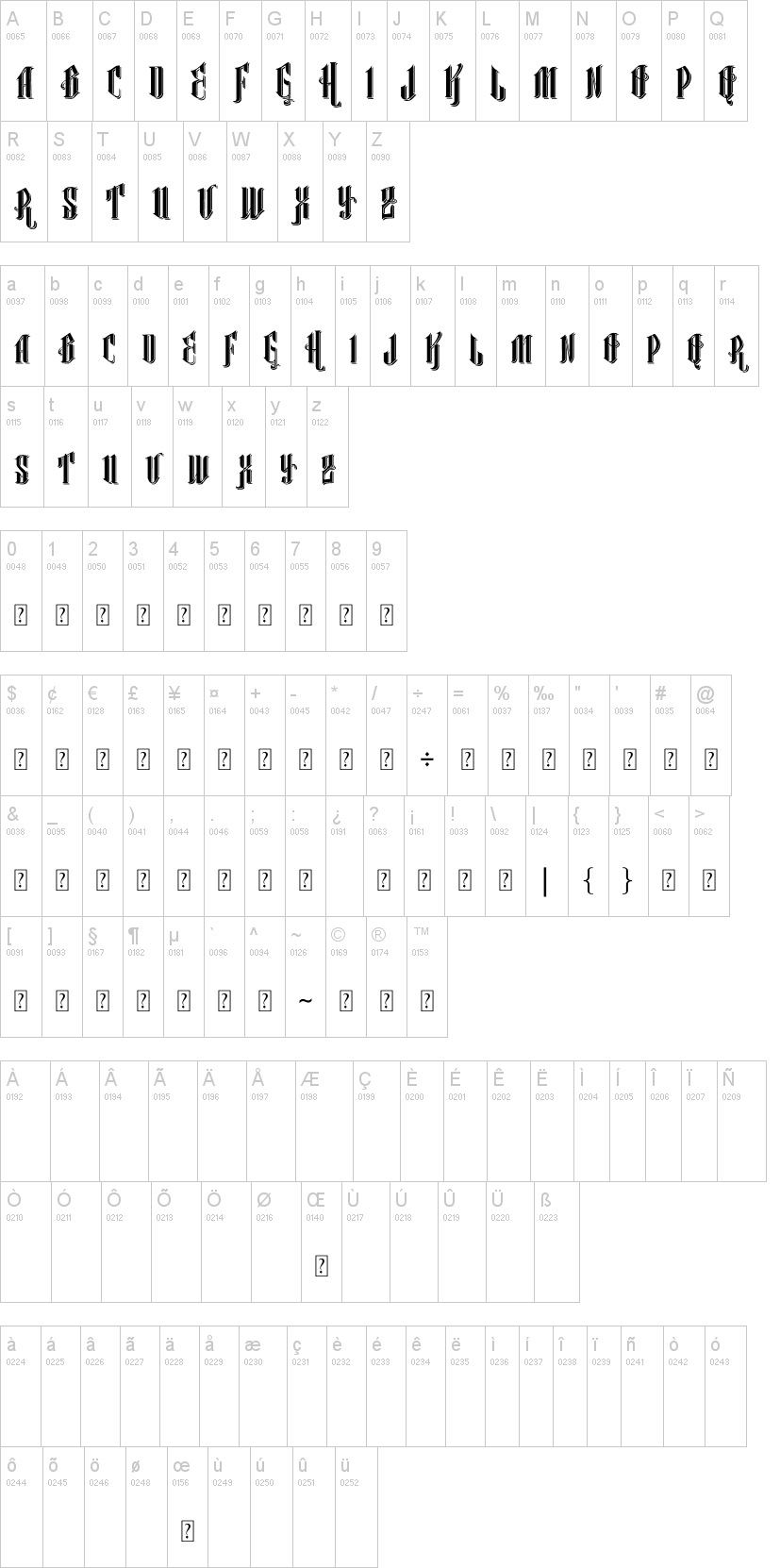
Vtks Classical Hit
Vtks Classical Hit是一种免费的字体,具有古典艺术品的外观和感觉。它的风格模仿了手写书法,但展现了现代化的特点,包括清晰的线条和粗糙的笔触。该字体适用于标题、标志、海报和其他需要突出效果的设计项目。由于其独特的样式和设计,它可以提高设计作品的可读性和吸引力,同时也为设计师提供了一个创新和有趣的选择。
Vtks Classical Hit是一款非常不错的手写艺术字体,具有很好的视觉感,适合于文化类的宣传设计、商业类品牌的广告和产品包装设计以及个性化文字排版等较多场景。